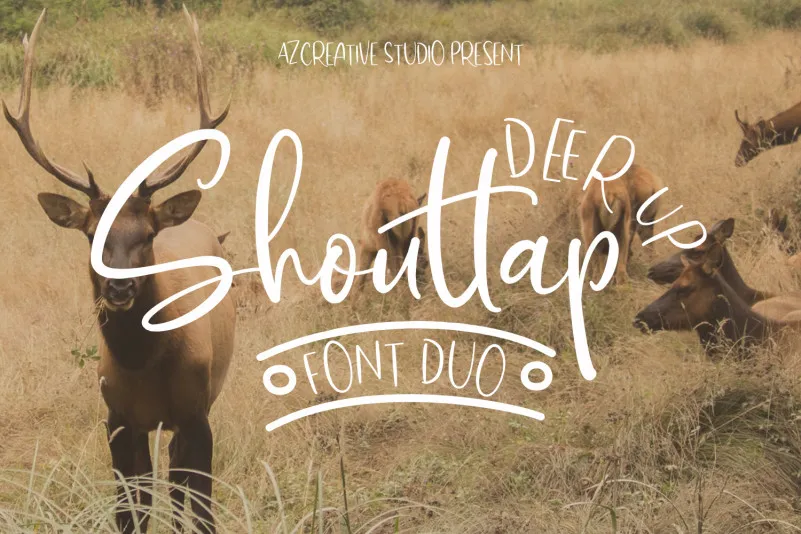
Esta é uma bela fonte escrita à mão que combina perfeitamente a elegância do tipo gótico com os tracinhos fluidos dos tipos escritos à mão. Ela traz extras adoráveis e contém caracteres PUA, o que lhe dá um poder de personalização sem precedentes. Esta versatilidade significa que esta fonte pode ser usada em uma variedade de aplicações, desde logotipos até embalagens, com a única limitação sendo sua própria imaginação. A ‘DeerUp Shouttap Font’ é uma escolha perfeita para designers buscando algo único e criativo para seus projetos.